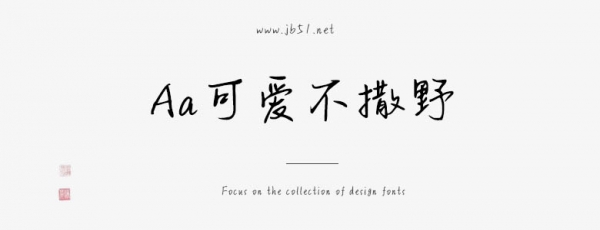
Aa可愛不撒野是一款不錯的藝術(shù)字體,由Aa字庫出品,字體筆觸纖細(xì),書寫流暢,擁有字符數(shù)8028和字形數(shù)8008,具有很好的視覺感,適合應(yīng)用于藝術(shù)設(shè)計(jì)、平面宣傳設(shè)計(jì)、網(wǎng)頁設(shè)計(jì),書法字帖等領(lǐng)域,需要的朋友可以前來本站下載。